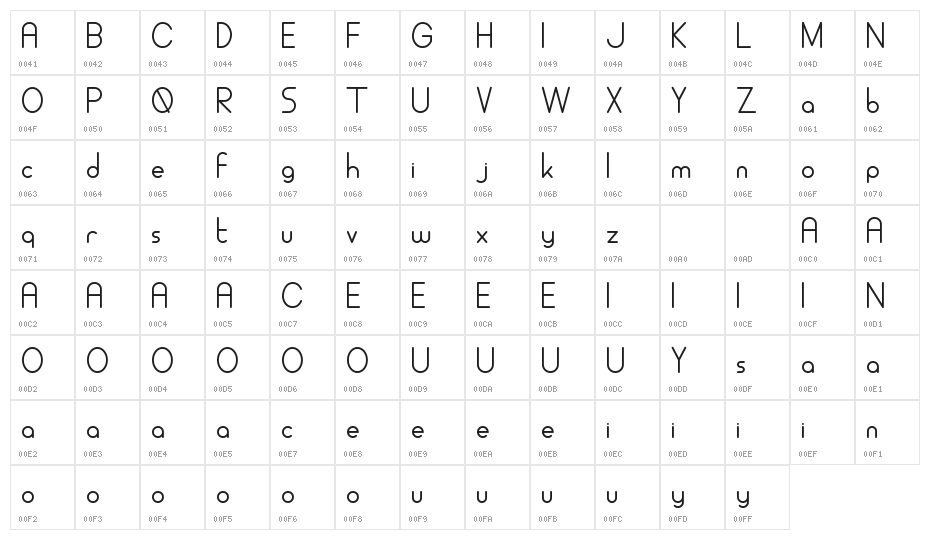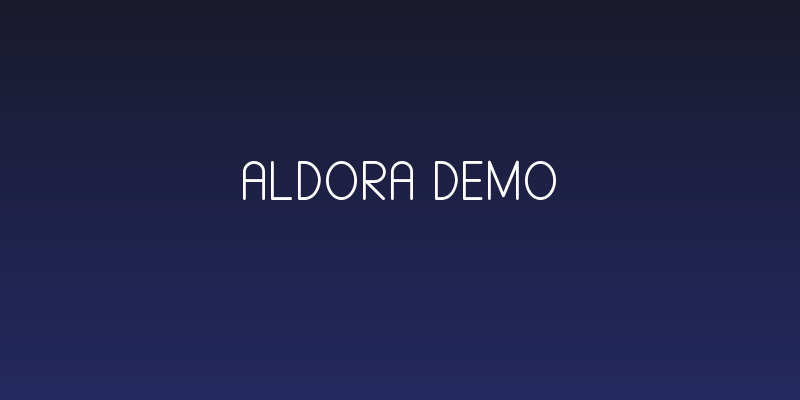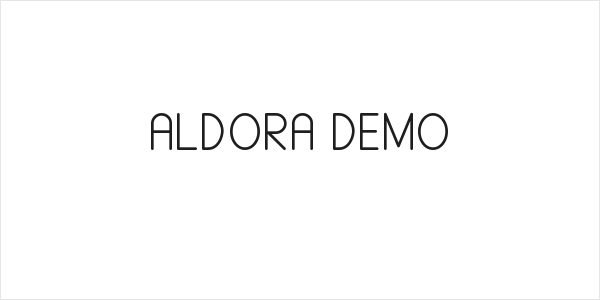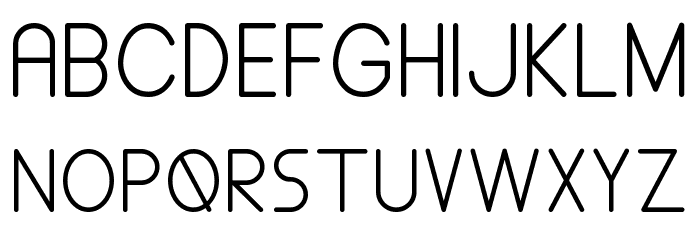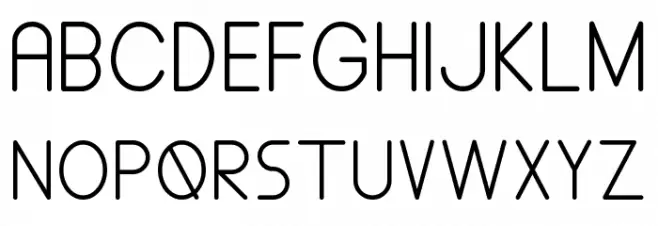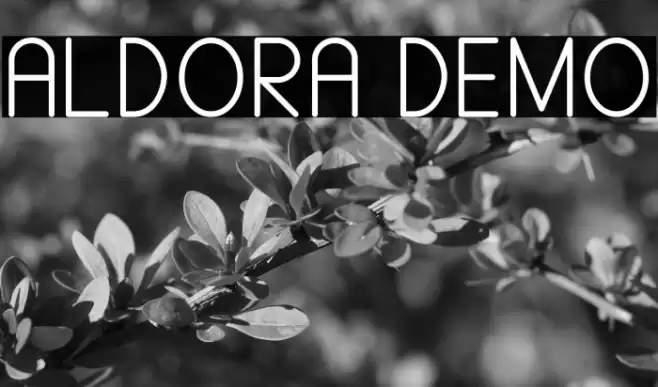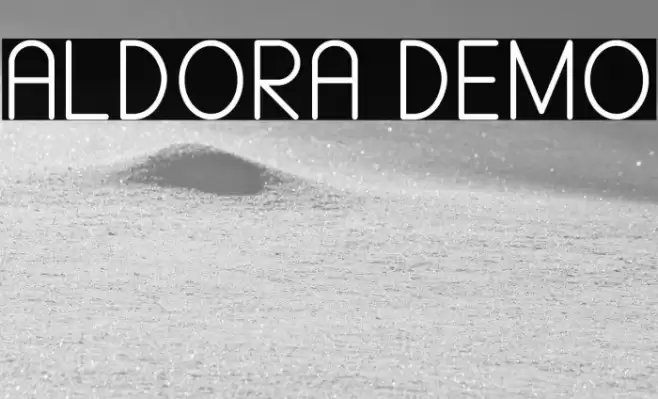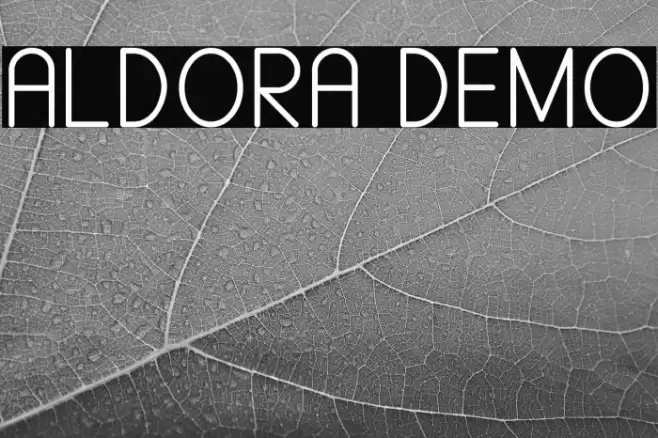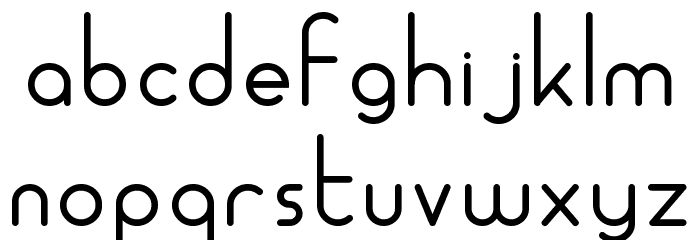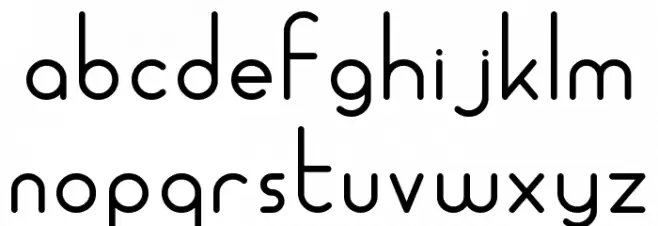
ALDORA DEMO Font
| Caso d'uso | Headlines, Logos, Digital Media |
| Progetti proposti | Ideal for branding, advertising, and digital media projects that require a modern and approachable look. |